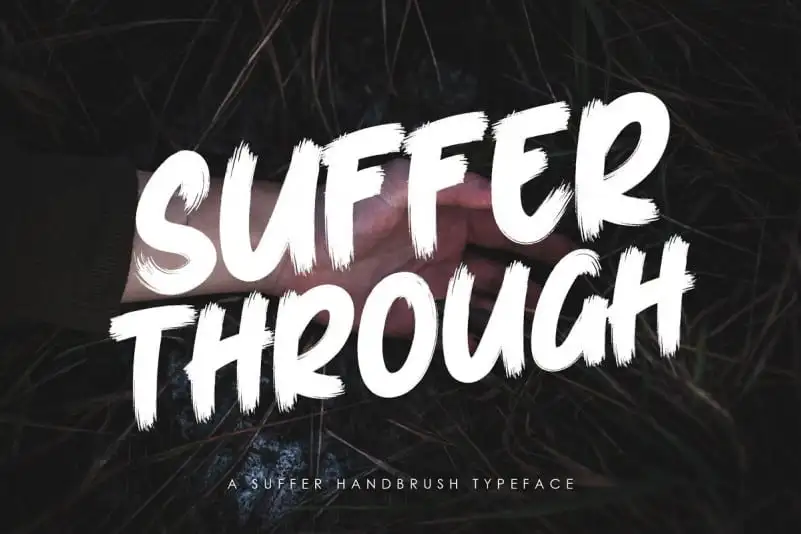
Suffer Through Brush Font – Download Grátis
A Suffer Through Brush Font é uma fonte totalmente única criada por Crump Hand, designer responsável pelo estilo elegante e autêntico de escrita à mão. Ela é um tipo brush font projetado com textura transparência, o que adiciona um toque especial ao design. Uma das suas características inovadoras inclui extra underlines e também uma textura splatter em psd e vetor, que se adequam a qualquer projeto de design. Esta fonte oferece aquele toque a mais para tornar seu trabalho ainda mais incrível. É perfeita para designers buscando dar um pouco de personalidade única à sua criação. Com o Suffer Through Brush Font, você pode criar designs de alta qualidade com um estilo autêntico e moderno.